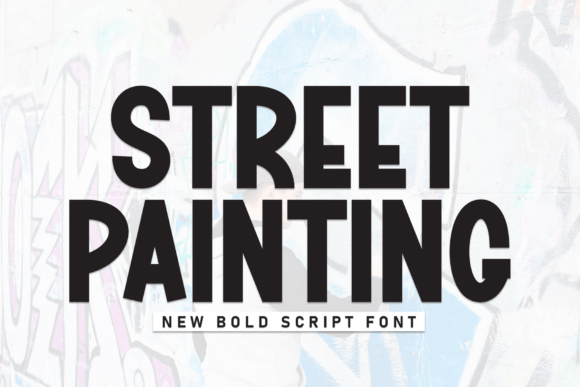
Street Painting
Street Paintingのような高品質の素材をお探しの場合、このプレミアムパッケージはクリエイティブなプロジェクトに素晴らしい選択です。
POD(オンデマンド印刷)製品、結婚式の招待状、またはソーシャルメディアのグラフィックを作成している場合でも、Street Paintingは理想的です。